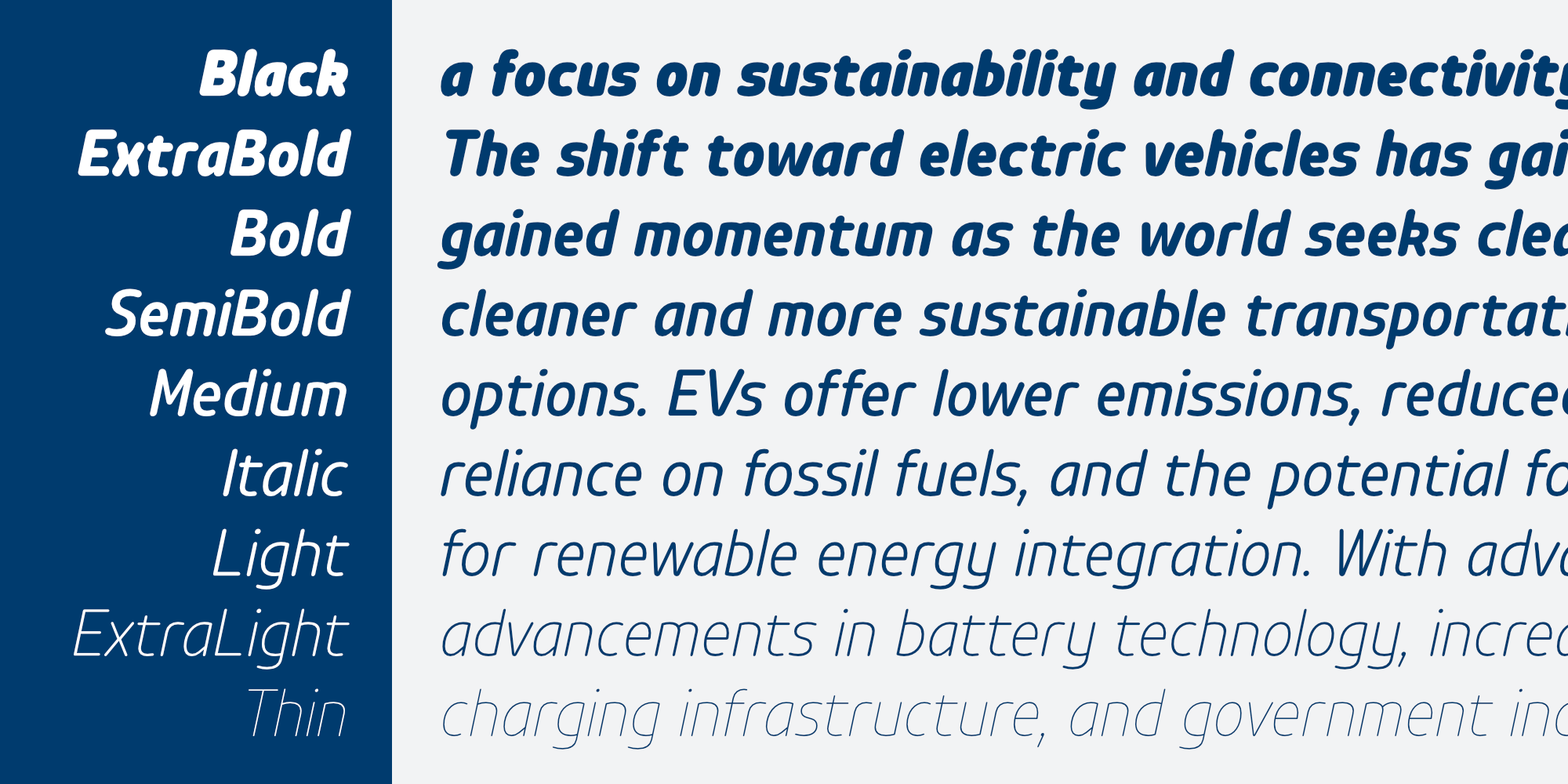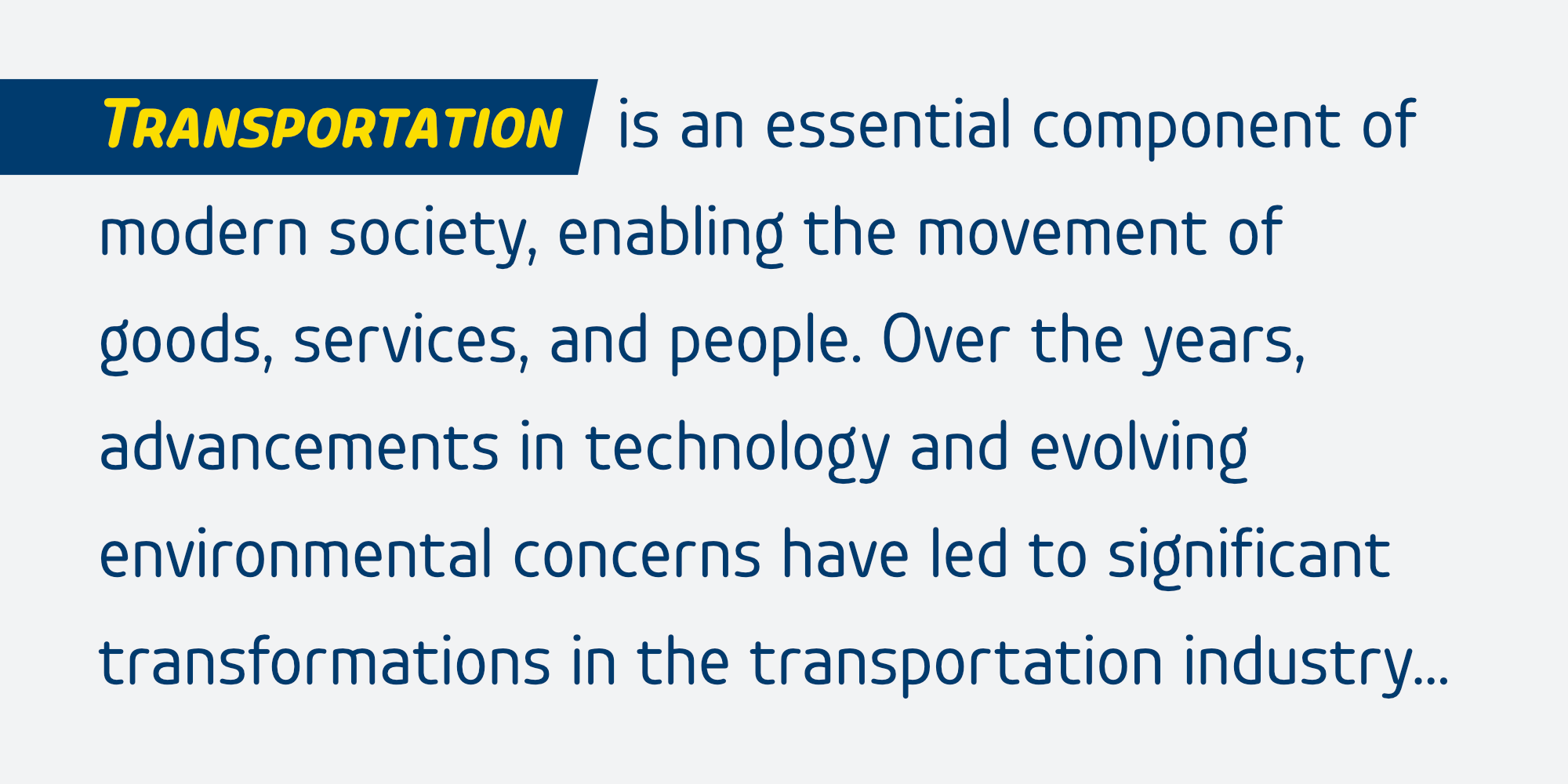
ขนส่ง ราวนด์ | Khonsong Rounded
ชื่อฟอนต์ : ขนส่ง ราวนด์ | Khonsong Rounded
ขอแนะนำฟอนต์ Khonsong Rounded ฟอนต์กลมมนแบบ semi-condensed sans serif ซึ่งผสมผสานความทันสมัย อนาคต และความนุ่มละมุนเข้าด้วยกันอย่างกลมกลืน ด้วยรูปลักษณ์ที่โฉบเฉี่ยวและร่วมสมัย ความกว้างแบบ semi-condensed ทำให้มีความสมดุลที่สมบูรณ์แบบระหว่างการประหยัดพื้นที่และความสามารถในการอ่าน ทำให้เป็นตัวเลือกที่เหมาะสำหรับการใช้งานที่หลากหลาย ตั้งแต่สื่อออนไลน์ไปจนถึงสื่อสิ่งพิมพ์
Introducing "Khonsong Rounded" a rounded semi-condensed sans serif font that embodies a harmonious blend of modernity, futurism and softness. With its sleek and contemporary appearance, Its semi-condensed proportions strike a perfect balance between space-saving efficiency and legibility, making it an ideal choice for various applications,  from online media to print media.